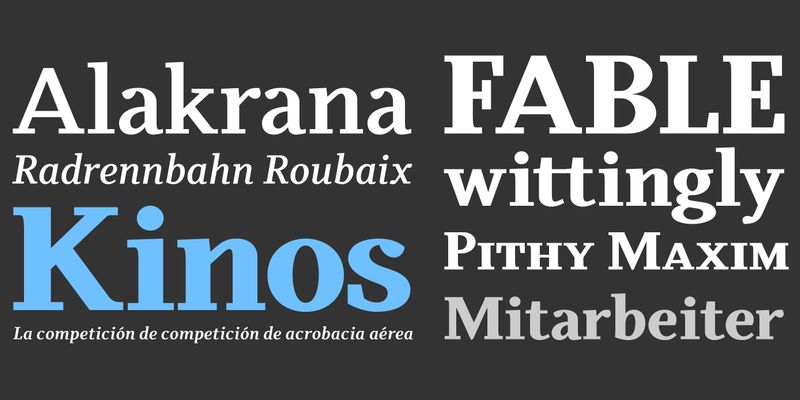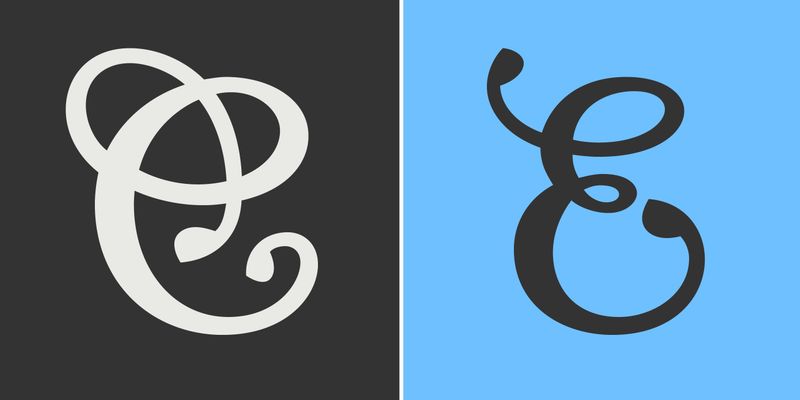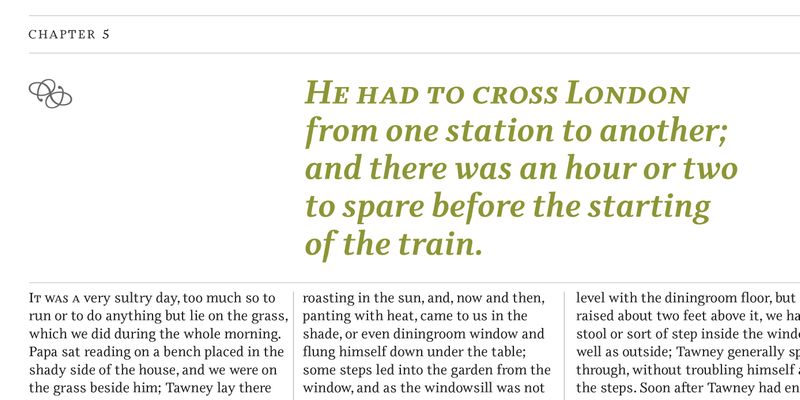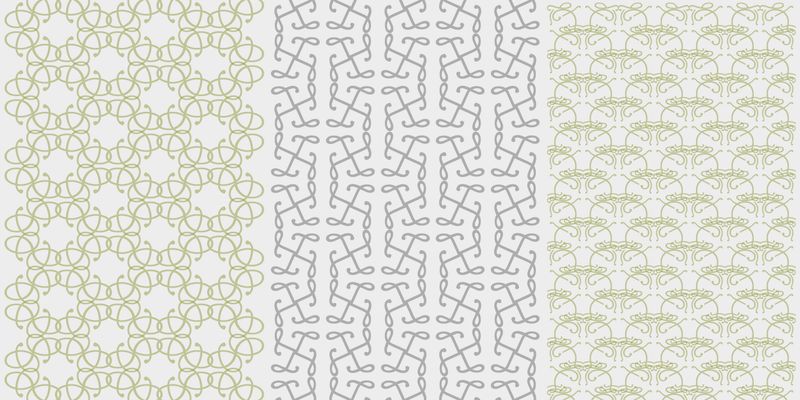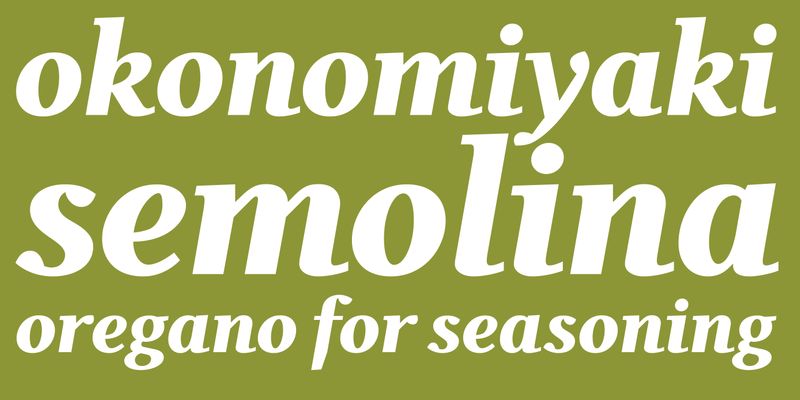
Odile ist eine Textschrift mit eingeklammertem Kopf und klammerlosen unteren Serifen – eine Eigenschaft, die der Starrheit der meisten traditionellen Slab-Serif-Schriften entgegenwirkt. Dieses zeitgenössische Design ist inspiriert von einer experimentellen Schrift namens Charter, die ursprünglich von dem amerikanischen Buch- und Schriftdesigner William Addison Dwiggins entworfen wurde.
Dwiggins plante Charter als kursives Gegenstück zu Arcadia, Experimental No. 221. Das Charter-Projekt kam nur in kleinen Schritten voran, geriet während des Zweiten Weltkriegs ins Stocken und kam 1955 zum Stillstand. In Anbetracht des skurrilen Designs von Charter wurden die Fragmente neu überdacht und zu einer umfassenden Textfamilie entwickelt.
Odile Upright Italic zeigt sichtbare Gemeinsamkeiten mit Dwiggins’ Charter und definiert den Gestaltungsansatz für die Familie. Der steile kalligrafische Aufstrich und die niedrigen Übergänge vom Schaft wie bei der aufrechten Kursiv „h” oder „m” werden in der Kursiv allmählich abgeschwächt und für die römischen Schriftstärken nach oben verschoben.
Die sechs optisch ausgewogenen Schriftstärken reichen von der zarten Light bis zur kräftigen Black, begleitet von Display-Varianten mit fließendem Flair und feurigen Ornamenten. Zwei Arten von Initialen – die eine verstärkt mit verschlungenen Schwüngen, die andere zurückhaltender – sind eindeutig von der Upright Italic abgeleitet. Die anmutige Serifenschrift harmoniert perfekt mit Elido, Odiles serifenlosem Pendant.